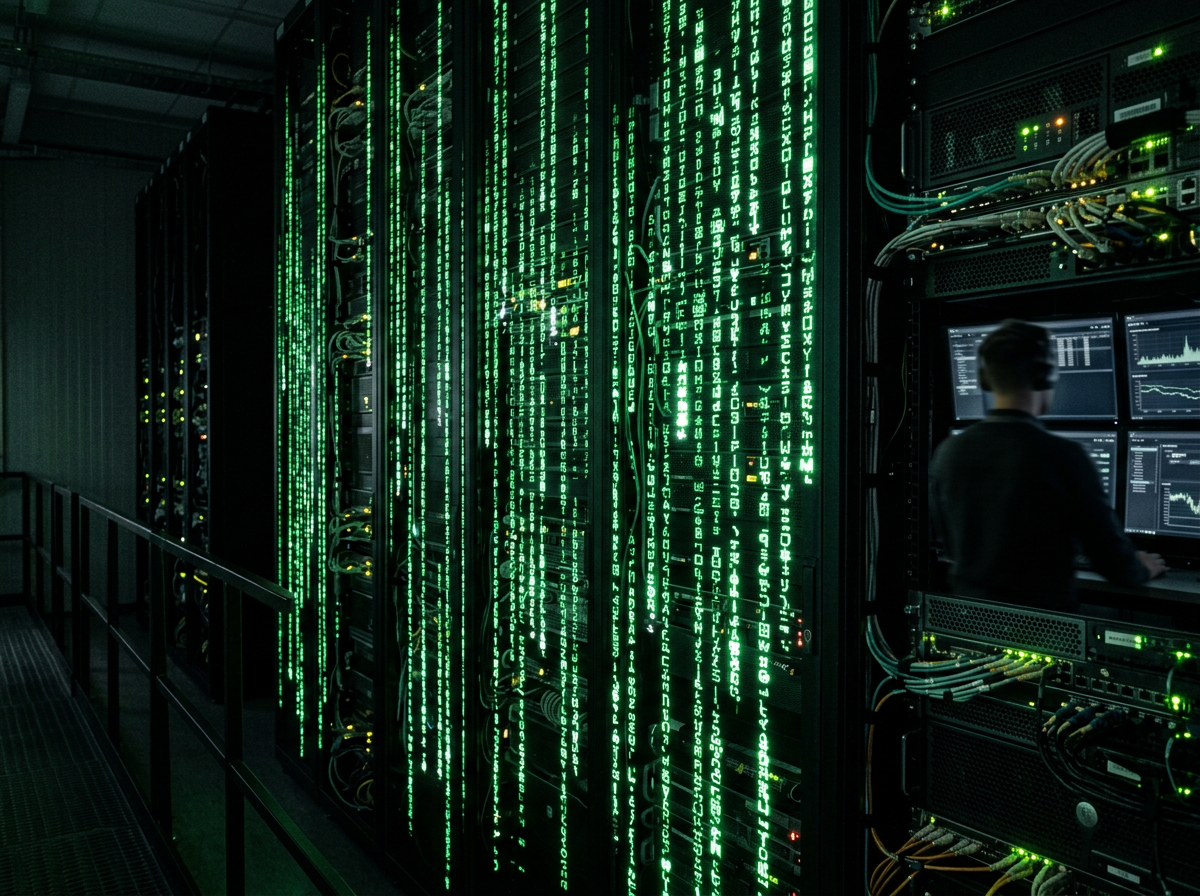
Matrix-ähnliche Schriftarten – 10 Alternativen
Die Ästhetik des Matrix-Films prägte eine ganze Generation. Besonders die ikonische Schriftart, die den digitalen Regen im Film darstellt, fasziniert bis heute. Doch welche Schriftarten vermitteln eigentlich diesen futuristischen und zugleich rätselhaften Eindruck?
Dieser Artikel beleuchtet die charakteristischen Merkmale der Matrix-Typografie und stellt zehn Alternativen vor. Diese Schriften eignen sich hervorragend, um in eigenen Projekten eine ähnliche Atmosphäre zu schaffen.
Dabei geht es nicht nur um die reine Optik, sondern auch um die semantische Wirkung, die solche Schriften auf den Betrachter haben. Ein tieferes Verständnis der Designprinzipien hilft, die passende Wahl zu treffen.
Was macht die Matrix-Schriftart so einzigartig und wiedererkennbar?
Die Matrix-Schriftart, oft als „Matrix Code“ bezeichnet, ist in ihrer Filmrepräsentation eine stark verfremdete Version der Lucidatypewriter. Ihre Einzigartigkeit rührt von der Kombination aus einem Monospace-Design und der visuellen Darstellung als herabrieselnde, grüne Zeichenkette her, die ein Gefühl von digitaler Immersion und Komplexität vermittelt.
Diese visuelle Sprache transportiert nicht nur Informationen, sondern auch die zentrale Thematik des Films: die allgegenwärtige digitale Realität. Die Schriftart wirkt dabei gleichzeitig archaisch, wie aus einem alten Terminal, und hypermodern, als Symbol einer fortgeschrittenen KI.
Der Film „Matrix“ von 1999 etablierte eine neue Ästhetik im Science-Fiction-Genre. Die visuelle Darstellung des Codes wurde zu einem kulturellen Phänomen.
Die Ursprünge der digitalen Ästhetik
Die ursprüngliche Schriftart für den Matrix-Code, von Simon Whiteley entworfen, ist eine abgewandelte Form der japanischen Katakana-Schriftzeichen, kombiniert mit lateinischen Buchstaben und arabischen Ziffern. Diese Mischung aus verschiedenen Schriftsystemen erzeugt eine exotische und kryptische Wirkung, die das Gefühl des unbekannten verstärkt.
Die Verwendung von Katakana, die oft für die Transkription fremdsprachiger Wörter dienen, unterstreicht die Idee einer fremden, übergeordneten Systematik. Dies verbindet sich mit der Filmhandlung, in der die Menschheit unwissentlich in einer simulierten Realität lebt.
Ein entscheidendes Merkmal ist auch die fallende Animation der Zeichen, die den „digitalen Regen“ bildet. Diese Bewegung verstärkt den Eindruck eines lebendigen, sich ständig verändernden Systems, das die Welt umgibt.
Charakteristische Merkmale des Matrix-Codes
Der Matrix-Code zeichnet sich durch mehrere typografische Attribute aus. Erstens ist er monospace, was bedeutet, dass alle Zeichen die gleiche breite haben. Dies erinnert an alte Computerterminals und Programmierumgebungen.
Zweitens ist die Farbgebung fast immer ein leuchtendes Grün auf schwarzem Hintergrund. Diese Farbkombination ist nicht nur ein direkter Verweis auf die Filmästhetik, sondern auch historisch mit den Phosphorbildschirmen früherer Computer verbunden.
Drittens sind die Zeichen oft leicht verzerrt oder unvollständig dargestellt, was den Eindruck von Datenfluss und digitaler Störung verstärkt. Diese subtilen Details tragen maßgeblich zur Gesamtwirkung bei und machen den Code so ikonisch.
Wichtig zu wissen
Die Matrix-Ästhetik beeinflusste nicht nur die Filmindustrie, sondern auch die digitale Kunst und das UI/UX-Design. Viele moderne Benutzeroberflächen greifen Elemente dieser digitalen Symbolik auf, um Futurismus oder technologische Kompetenz zu signalisieren.
Welche Schriftarten ähneln dem Matrix-Stil und eignen sich für Designprojekte?
Für Designprojekte, die eine ähnliche Atmosphäre wie der Matrix-Film erzeugen sollen, gibt es zahlreiche Schriftarten, die sich durch Monospace-Eigenschaften, digitale Anmutung oder eine futuristische Ästhetik auszeichnen. Diese Schriften variieren in ihrer Stärke der Ähnlichkeit, bieten aber alle eine Basis für den gewünschten Look.
Die Auswahl hängt stark vom spezifischen Kontext ab. Soll es eine direkte Anspielung sein oder lediglich eine subtile Referenz? Ein mit einem Schriftgenerator lassen sich solche Effekte oft schnell testen und anpassen.
Manchmal reicht schon eine spezielle Farbgebung oder eine leichte Verzerrung, um den gewünschten Effekt zu erzielen, ohne eine exakte Kopie zu verwenden.
Monospace-Schriften als Basis
Monospace-Schriften sind eine hervorragende Grundlage, da sie die charakteristische gleichmäßige Zeichenbreite des Matrix-Codes aufweisen. Beispiele hierfür sind:
• IBM Plex Mono: Eine moderne, gut lesbare Monospace-Schrift, die eine klare technische Anmutung besitzt.
• Fira Code: Diese Schriftart ist besonders bei Programmierern beliebt und bietet Ligaturen, die Code noch lesbarer machen, aber auch einen digitalen Look vermitteln.
• Source Code Pro: Eine Open-Source-Schrift von Adobe, die für ihre Klarheit und gute Lesbarkeit in digitalen Umgebungen geschätzt wird.
Diese Schriften vermitteln eine professionelle und technische Ästhetik. Sie sind ideal für Benutzeroberflächen, Code-Darstellungen oder technische Dokumentationen, wo Klarheit und Struktur im Vordergrund stehen.
Futuristische und digitale Schriften
Neben reinen Monospace-Schriften gibt es auch viele, die durch ihre Formgebung direkt eine futuristische oder digitale Stimmung erzeugen. Diese Schriften spielen oft mit geometrischen Formen, scharfen Kanten oder Segmenten.
• Orbitron: Eine geometrische Sans-Serif-Schrift, die speziell für Science-Fiction-Filme und Displays entwickelt wurde.
• Digital-7: Diese Schriftart imitiert den Look von LCD-Displays und ist perfekt für die Darstellung von Zahlen oder kurzen Texten im digitalen Stil.
• Eurostile: Eine klassische Schriftart, die seit Jahrzehnten in Science-Fiction-Kontexten verwendet wird und eine starke, technologische Präsenz hat.
Solche Schriften eignen sich gut für Titel, Logos oder kurze Slogans, bei denen die visuelle Wirkung entscheidend ist. Sie können schnell eine futuristische oder technologische Assoziation hervorrufen.
Schriften mit Glitch- oder Störungs-Effekten
Manche Schriftarten integrieren bereits Effekte, die an digitale Störungen oder „Glitches“ erinnern. Diese sind besonders wirkungsvoll, um die unvollkommene, aber faszinierende Natur des Matrix-Codes zu imitieren.
• Broken Console: Eine Schriftart, die den Eindruck erweckt, als käme sie von einem beschädigten Terminal.
• Matrix Code NFI: Eine freie Schriftart, die direkt von der Filmästhetik inspiriert ist und die fallenden Zeichen imitiert.
• Cyberpunk: Diese Kategorie von Schriften umfasst oft verzerrte oder fragmentierte Buchstaben, die eine dystopische Zukunft suggerieren.
Der Einsatz solcher Schriften sollte jedoch sparsam erfolgen, da sie die Lesbarkeit stark beeinträchtigen können. Sie sind am besten für kurze, prägnante Überschriften oder künstlerische Elemente geeignet.
Gibt es freie Alternativen zur Matrix-Schrift für kommerzielle Projekte?
Ja, es gibt eine Vielzahl von freien Schriftarten, die dem Matrix-Stil ähneln und auch für kommerzielle Projekte genutzt werden dürfen. Viele Designer stellen ihre Kreationen unter Open-Source-Lizenzen wie der SIL Open Font License (OFL) zur Verfügung, was eine kostenfreie Nutzung und Modifikation ermöglicht.
Es ist jedoch von entscheidender Bedeutung, die Lizenzbedingungen jeder Schriftart genau zu prüfen. Nicht alle „kostenlosen“ Schriften erlauben eine kommerzielle Nutzung oder die Einbettung in Webseiten oder Apps.
Plattformen wie Google Fonts oder Font Squirrel bieten eine große Auswahl an lizenzfreien Schriften, die man nach bestimmten Kriterien filtern kann. Dort findet man oft hochwertige Alternativen, die dem gewünschten Look nahekommen.
Ressourcen für kostenlose Schriften
Einige der besten Quellen für kostenlose und kommerziell nutzbare Schriften sind:
• Google Fonts: Bietet eine riesige Bibliothek an Webfonts, die alle unter der Open Font License stehen. Hier finden sich viele Monospace- und geometrische Schriften.
• Font Squirrel: Kuratiert nur Schriften, die für kommerzielle Zwecke kostenlos sind und bietet gute Filteroptionen.
• DaFont: Eine große Sammlung von Schriften, bei der man die Lizenz (z.B. „100% Free“ oder „Free for personal use“) genau prüfen muss.
Beim Download ist es wichtig, die beigelegten Lizenzdateien zu speichern und zu archivieren. So kann man im Zweifelsfall immer nachweisen, dass die Nutzung rechtmäßig ist.
Anpassung und Modifikation
Manchmal findet man keine perfekte Schrift, die alle Anforderungen erfüllt. In solchen Fällen kann man eine bestehende freie Schriftart modifizieren, sofern die Lizenz dies erlaubt. Kleine Anpassungen wie die Stärke der Striche, die Zeichenabstände oder leichte Verzerrungen können bereits eine große Wirkung erzielen.
Tools zur Schriftbearbeitung oder Vektorgrafikprogramme ermöglichen solche Modifikationen. Man kann auch eigene Effekte hinzufügen, wie zum Beispiel einen leichten Glitch-Effekt oder eine neonfarbene Kontur, um den digitalen Look zu verstärken.
Eine weitere Möglichkeit ist die Verwendung von CSS-Filtern oder JavaScript, um dynamische Effekte auf Web-Schriften anzuwenden. Dies erlaubt eine flexible Gestaltung, ohne die Grundschrift zu verändern.
Vor- und Nachteile: Die Ursprünge der digitalen Ästhetik Die ursprüngliche Schriftart für den Matrix-Code,
Vorteile
• Kostenersparnis durch freie Lizenzen.
• Große Auswahl an ähnlichen Stilen.
• Möglichkeit zur Modifikation unter passender Lizenz.
Nachteile
• Lizenzprüfung ist unerlässlich.
• Manchmal geringere Qualität oder Zeichenumfang.
• Eventuell zusätzliche Bearbeitung notwendig.
Welche Rolle spielen Farbe und Animation bei der Matrix-Ästhetik?
Die Farbe Grün und die Animation des fallenden Codes sind untrennbar mit der Matrix-Ästhetik verbunden und spielen eine ebenso wichtige Rolle wie die Schriftart selbst. Ohne diese Elemente würde selbst die perfekte Schriftart nicht die gleiche Wirkung entfalten. Die Kombination schafft eine immersive und dynamische Erfahrung.
Der grüne Farbton auf schwarzem Hintergrund ist nicht zufällig gewählt; er erinnert an die Monochrom-Monitore der 80er-Jahre und symbolisiert gleichzeitig das digitale und Künstliche. Die Animation wiederum vermittelt den Eindruck eines lebendigen, fließenden Datenstroms.
Ein Designprojekt, das den Matrix-Stil aufgreifen möchte, sollte daher nicht nur die Schriftart, sondern auch Farbe und Bewegung berücksichtigen. Diese Elemente arbeiten zusammen, um eine kohärente und überzeugende digitale Welt zu erschaffen.
Die Bedeutung der grünen Farbgebung
Das charakteristische Matrix-Grün ist mehr als nur eine Farbe; es ist ein Symbol. Es steht für die digitale Welt, die Illusion und die künstliche Natur der Matrix. Der Farbton ist oft ein helles, fast schon neonartiges Grün, das einen starken Kontrast zum tiefen Schwarz des Hintergrunds bildet.
Diese Farbwahl erzeugt eine unheimliche und zugleich faszinierende Atmosphäre. Es ist eine Farbe, die man sofort mit Technologie, Daten und einer gewissen Kälte assoziiert. Die psychologische Wirkung von Grün kann auch eine Verbindung zur Natur herstellen, hier jedoch in einer pervertierten, synthetischen Form.
Einige Studien zur Farbpsychologie zeigen, dass Grün beruhigend wirken kann, aber in diesem Kontext wird es durch den Kontrast und die Animation zu einem Symbol der ständigen, unaufhörlichen Aktivität.
Animation und dynamische Effekte
Die Animation des fallenden Codes ist das visuelle Herzstück der Matrix-Ästhetik. Sie vermittelt den Eindruck von Datenfluss, Komplexität und einer sich ständig aktualisierenden Realität. Ohne diese Bewegung wäre der Code statisch und würde viel von seiner Wirkung verlieren.
Für eigene Projekte kann man ähnliche Effekte mit CSS-Animationen, JavaScript oder Video-Elementen erzielen. Dabei geht es nicht nur um das einfache Herunterfallen von Zeichen, sondern auch um subtile Variationen in Geschwindigkeit, Transparenz und Verzerrung.
Ein gut umgesetzter Animationseffekt kann die Immersion des Betrachters erheblich steigern und das Gefühl vermitteln, in eine digitale Welt einzutauchen. Die Entwicklung visueller Effekte hat hier enorme Fortschritte gemacht.
Kurz gesagt: Farbe und Animation sind für die Matrix-Ästhetik ebenso entscheidend wie die Schriftart selbst, da sie den digitalen und immersiven Charakter verstärken.
Welche typografischen Tricks verstärken den Matrix-Look?
Über die reine Schriftart hinaus gibt es verschiedene typografische Tricks und Designtechniken, die den Matrix-Look in Projekten verstärken können. Es geht darum, die visuellen Eigenheiten des Films zu verstehen und sie gezielt einzusetzen. Ein einfacher Text kann so in eine digitale Datenstrom-Ästhetik verwandelt werden.
Man muss nicht immer die exakte Schriftart finden; oft reicht es, bestimmte Effekte zu imitieren. Dies spart Zeit und ermöglicht eine größere Flexibilität im Designprozess. Die Kombination mehrerer kleiner Anpassungen führt oft zum besten Ergebnis.
Ein bewusster Einsatz von Kontrast, Transparenz und Überlagerungen kann die gewünschte Wirkung erzeugen. Selbst subtile Änderungen in der Textdarstellung können eine starke Assoziation hervorrufen.
Monospacing und Zeichenabstände
Auch wenn eine gewählte Schriftart nicht von Natur aus monospace ist, kann man durch manuelle Anpassung der Zeichenabstände (Kerning und Tracking) einen ähnlichen Effekt erzielen. Das Ziel ist eine gleichmäßige Verteilung der Zeichen, die an alte Terminal-Ausgaben erinnert.
Ein konstanter Zeichenabstand über alle Buchstaben hinweg schafft eine geordnete, technische Anmutung. Dies ist besonders wichtig für Code-Darstellungen oder wenn man das Gefühl eines Computerbildschirms vermitteln möchte.
Manchmal kann auch ein leicht erhöhter Zeilenabstand (Leading) dazu beitragen, den Text luftiger und „codelastiger“ wirken zu lassen. Dies imitiert den vertikalen Fluss des Matrix-Codes.
Farbverläufe und Leuchteffekte
Anstatt nur eine feste grüne Farbe zu verwenden, können subtile Farbverläufe oder Leuchteffekte den digitalen Charakter verstärken. Ein leichter Glanz oder ein pulsierender Effekt kann den Eindruck erwecken, dass der Text „lebt“ oder „arbeitet“.
Man kann auch mit unterschiedlichen Grüntönen innerhalb eines Textblocks spielen, um eine größere tiefe zu erzeugen. Ein helleres Grün für aktive Elemente und ein dunkleres für Hintergrundinformationen kann hier sinnvoll sein.
Die Verwendung von Schattenwürfen oder „Glow“-Effekten um die Buchstaben herum kann ebenfalls den Eindruck eines digitalen Displays verstärken. Diese Effekte sind besonders wirkungsvoll bei dunklen Hintergründen.
Praxis-Tipp
Experimentieren Sie mit der Deckkraft von Textschichten. Eine leicht transparente Textschicht, die sich über ein Hintergrundbild oder eine Animation legt, kann die Illusion eines digitalen Overlays erzeugen, ähnlich wie im Film.
Ein weiterer Trick ist die Überlagerung von Texten. Man kann zwei leicht versetzte Textschichten mit unterschiedlichen Transparenzen oder Farben übereinanderlegen, um einen subtilen Glitch-Effekt zu simulieren. Dies erzeugt eine visuelle Unruhe, die an digitale Störungen erinnert.
Die Wahl der richtigen Schriftgröße ist ebenfalls entscheidend. Ein zu kleiner Text mit vielen Effekten wird unleserlich, während ein zu großer Text schnell überladen wirken kann. Eine Balance zwischen Ästhetik und Funktionalität ist hier der Schlüssel.
EffektBeschreibung
MonospacingGleichmäßige Zeichenbreite für technische Anmutung.
Grüne FarbpaletteNeon- oder hellgrüne Töne auf dunklem Hintergrund.
LeuchteffekteSubtiler Glanz oder „Glow“ um die Buchstaben.
TransparenzLeichte Deckkraft für Überlagerungseffekte.
Weitere Inhalte dieser Website
Häufige Fragen
Welche Schriftart ist die originale Matrix-Schrift?
Die originale Matrix-Schriftart, die im Film für den „digitalen Regen“ verwendet wird, basiert auf einer modifizierten Version der japanischen Katakana-Schriftzeichen , kombiniert mit lateinischen Buchstaben und arabischen Ziffern. Sie wurde von Simon Whiteley entworfen und ist keine direkt verfügbare Standard-Schriftart.
Kann man die Matrix-Schriftart kostenlos herunterladen und nutzen?
Direkt die exakte Film-Schriftart ist nicht frei verfügbar. Es gibt jedoch zahlreiche ähnliche Schriftarten und Nachbildungen , die kostenlos heruntergeladen und oft auch kommerziell genutzt werden dürfen. Man sollte stets die Lizenzbedingungen der jeweiligen Schriftart prüfen, um rechtliche Probleme zu vermeiden.
Welche Eigenschaften sollte eine Matrix-ähnliche Schrift haben?
Eine Matrix-ähnliche Schrift sollte idealerweise monospace sein, also eine feste Zeichenbreite besitzen, und eine digitale oder futuristische Anmutung aufweisen. Oft sind geometrische Formen, scharfe Kanten oder segmentierte Buchstaben charakteristisch. Eine grüne Farbgebung auf dunklem Hintergrund verstärkt den Effekt zusätzlich.
Für welche Projekte eignen sich Matrix-ähnliche Schriftarten am besten?
Matrix-ähnliche Schriftarten eignen sich hervorragend für Science-Fiction-Projekte, technische Benutzeroberflächen, Gaming-Designs, Film-Titelsequenzen oder futuristische Logos . Sie sind ideal, um eine Atmosphäre von Technologie, Code, Virtualität oder Dystopie zu erzeugen.
Gibt es Alternativen zu den bekannten Matrix-ähnlichen Schriften?
Ja, neben den direkten Nachbildungen gibt es viele Monospace-Schriften wie IBM Plex Mono oder Source Code Pro , die eine klare, technische Basis bieten. Auch futuristische Schriften wie Orbitron oder Eurostile können eine ähnliche Wirkung erzielen, wenn sie entsprechend farblich und mit Effekten versehen werden.
Abschließende Gedanken zur digitalen Typografie
Die Suche nach ähnlichen Schriftarten wie im Matrix-Film ist mehr als nur eine stilistische Entscheidung; es ist eine Auseinandersetzung mit der visuellen Sprache des Futurismus und der digitalen Ära. Die Matrix-Ästhetik hat sich fest in unser kollektives Bewusstsein eingebrannt und dient als Referenzpunkt für alles, was mit Code, KI und virtuellen Welten zu tun hat.
Die Auswahl der richtigen Schriftart und die geschickte Anwendung von Farbe, Animation und typografischen Tricks ermöglichen es Designern, diese faszinierende Atmosphäre in ihren eigenen Projekten zu reproduzieren. Es geht darum, eine Geschichte zu erzählen und Emotionen zu wecken, die über den reinen Text hinausgehen.
Letztlich ist die digitale Typografie ein mächtiges Werkzeug. Sie kann die Wahrnehmung einer Botschaft fundamental beeinflussen und einem Projekt eine unverwechselbare Identität verleihen. Die Matrix-Schrift ist hierfür ein Paradebeispiel.